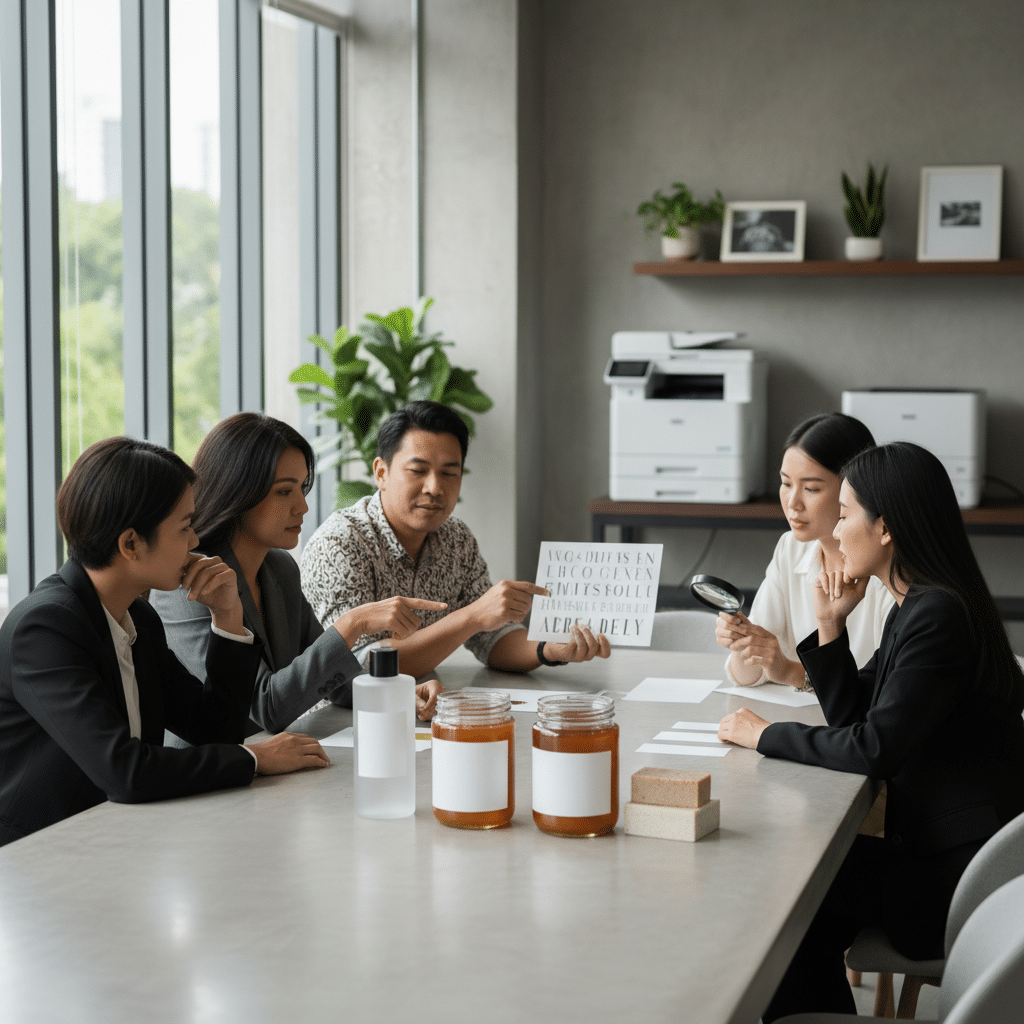
อัปเดต 2026! ทริคเลือกฟอนต์ฉลากสินค้าให้แบรนด์ดูแพง
การเลือกฟอนต์สำหรับฉลากสินค้าเป็นมากกว่าการเลือกตัวอักษรที่สวยงาม แต่คือกลยุทธ์สำคัญในการสื่อสารตัวตนของแบรนด์และสร้างการรับรู้ที่มีมูลค่าสูงในสายตาผู้บริโภค ฟอนต์ที่เหมาะสมสามารถยกระดับสินค้าธรรมดาให้ดูพรีเมียมและน่าเชื่อถือได้ ในทางกลับกัน ฟอนต์ที่เลือกผิดอาจทำให้แพ็กเกจจิ้งที่ออกแบบมาอย่างดีนั้นด้อยค่าลงได้ทันที
สรุปประเด็นสำคัญของการเลือกฟอนต์
- ความสอดคล้องกับแบรนด์: ฟอนต์ต้องสะท้อนบุคลิกและตำแหน่งทางการตลาดของสินค้าได้อย่างถูกต้อง เพื่อสร้างภาพลักษณ์ที่น่าเชื่อถือ
- ความเรียบง่าย: การใช้ฟอนต์ไม่เกิน 2-3 รูปแบบบนฉลากสินค้า ช่วยให้การออกแบบดูสะอาดตา เป็นระเบียบ และมีความพรีเมียม
- ความชัดเจนในการอ่าน: ฉลากสินค้าต้องให้ข้อมูลที่ชัดเจน ดังนั้นการเลือกฟอนต์ที่อ่านง่ายแม้มีขนาดเล็กจึงเป็นสิ่งสำคัญที่สุด
- การจัดวางอย่างมีชั้นเชิง: การใช้ขนาด น้ำหนัก และพื้นที่ว่างรอบตัวอักษรอย่างเหมาะสม ช่วยนำสายตาและสร้างความรู้สึกหรูหราให้กับการออกแบบ
- การเลือกตระกูลฟอนต์: ฟอนต์ตระกูล Serif ให้ความรู้สึกคลาสสิกและเป็นทางการ ในขณะที่ Sans-serif ให้ความรู้สึกทันสมัยและเรียบง่าย การเลือกใช้จึงขึ้นอยู่กับภาพลักษณ์ที่แบรนด์ต้องการสื่อสาร
เหตุผลที่ฟอนต์ส่งผลต่อภาพลักษณ์แบรนด์
ในโลกของการตลาดที่การแข่งขันสูง การสร้างแบรนด์ SME ให้โดดเด่นและเป็นที่จดจำนั้นมีความสำคัญอย่างยิ่ง ฉลากสินค้าเปรียบเสมือนด่านแรกที่สื่อสารกับลูกค้า และฟอนต์คือ “น้ำเสียง” ของแบรนด์ที่แสดงออกผ่านการออกแบบ ฟอนต์สามารถกระตุ้นความรู้สึกและสร้างการรับรู้ได้โดยที่ผู้บริโภคอาจไม่รู้ตัว เช่น ฟอนต์ที่มีเส้นสายโค้งมนอาจให้ความรู้สึกเป็นมิตรและเข้าถึงง่าย ในขณะที่ฟอนต์ที่มีเส้นตรง คมชัด อาจสื่อถึงความเป็นมืออาชีพ ความน่าเชื่อถือ และความทันสมัย
สำหรับผู้ประกอบการ การเลือกฟอนต์จึงเป็นขั้นตอนเชิงกลยุทธ์ที่ต้องพิจารณาอย่างรอบคอบในช่วงเริ่มต้นของการพัฒนาสินค้าหรือการปรับภาพลักษณ์แบรนด์ การเลือกฟอนต์ที่ไม่สอดคล้องกับบุคลิกของสินค้าอาจสร้างความสับสนและลดทอนความน่าเชื่อถือ เช่น การใช้ฟอนต์แนวสนุกสนานกับผลิตภัณฑ์สกินแคร์ระดับพรีเมียม อาจทำให้สินค้าดูไม่น่าไว้วางใจ ดังนั้น การทำความเข้าใจจิตวิทยาเบื้องหลังของฟอนต์แต่ละประเภทจึงเป็นเครื่องมือสำคัญที่ช่วยให้การออกแบบฉลากสินค้าสามารถเพิ่มมูลค่าและสร้างความประทับใจแรกที่แข็งแกร่งได้
หลักการพื้นฐานในการเลือกฟอนต์ฉลากสินค้าให้ดูแพง
การทำให้ฉลากสินค้าดู “แพง” ไม่ได้หมายถึงการเลือกใช้ฟอนต์ที่หรูหราหรือวิจิตรพิสดารเสมอไป แต่เกิดจากการผสมผสานองค์ประกอบหลายอย่างเข้าด้วยกันอย่างลงตัว เพื่อสร้างภาพรวมที่ดูดี มีรสนิยม และสื่อสารคุณค่าของแบรนด์ได้อย่างมีประสิทธิภาพ หลักการพื้นฐานต่อไปนี้เป็นแนวทางสำคัญสำหรับนักออกแบบและเจ้าของแบรนด์
จำกัดจำนวนฟอนต์: น้อยแต่มาก เรียบแต่โก้
หนึ่งในข้อผิดพลาดที่พบบ่อยในการออกแบบฉลากคือการใช้ฟอนต์หลากหลายรูปแบบมากเกินไป ซึ่งทำให้ฉลากดูสับสนและขาดความเป็นมืออาชีพ หลักการออกแบบสากลแนะนำให้จำกัดการใช้ฟอนต์บนชิ้นงานเดียวไว้ที่ไม่เกิน 2-3 รูปแบบ โดยแบ่งหน้าที่อย่างชัดเจน:
- ฟอนต์หลัก (Primary Font): ใช้สำหรับชื่อแบรนด์หรือชื่อสินค้า ซึ่งเป็นส่วนที่โดดเด่นที่สุด ควรเลือกฟอนต์ที่สะท้อนบุคลิกแบรนด์ได้ดีที่สุด
- ฟอนต์รอง (Secondary Font): ใช้สำหรับหัวข้อย่อยหรือคำอธิบายสั้นๆ ควรเป็นฟอนต์ที่เข้ากันได้ดีกับฟอนต์หลัก แต่อาจมีความแตกต่างเล็กน้อยเพื่อสร้างความน่าสนใจ
- ฟอนต์เนื้อหา (Body Font): ใช้สำหรับข้อมูลรายละเอียด เช่น ส่วนประกอบ วิธีใช้ หรือข้อมูลทางโภชนาการ ฟอนต์นี้ต้องเน้นความอ่านง่ายเป็นพิเศษ
การจำกัดจำนวนฟอนต์ช่วยสร้างความเป็นระเบียบและความต่อเนื่อง ทำให้ผู้บริโภคสามารถประมวลผลข้อมูลบนฉลากได้ง่ายขึ้น และยังส่งผลให้ภาพรวมของการออกแบบดูสะอาดตาและพรีเมียม
ความสอดคล้องกับบุคลิกของแบรนด์
ก่อนจะเลือกฟอนต์ สิ่งสำคัญคือต้องกำหนดบุคลิกของแบรนด์ (Brand Personality) ให้ชัดเจนก่อน แบรนด์ของคุณเป็นแบบไหน? คลาสสิก, ทันสมัย, ออร์แกนิก, สนุกสนาน, หรือหรูหรา? ฟอนต์ที่เลือกใช้ควรเป็นภาพสะท้อนของบุคลิกนั้นๆ
ฟอนต์ทำหน้าที่เปรียบเสมือน “เสียง” ของแบรนด์ การเลือกใช้ฟอนต์ที่ไม่เข้ากันก็เหมือนกับการพูดด้วยน้ำเสียงที่ไม่สอดคล้องกับข้อความที่ต้องการสื่อ ซึ่งจะทำให้ภาพลักษณ์ของแบรนด์ขาดความน่าเชื่อถือได้
ตัวอย่างเช่น สินค้าที่เป็นมิตรต่อสิ่งแวดล้อมอาจเหมาะกับฟอนต์ที่ให้ความรู้สึกเป็นธรรมชาติและเขียนด้วยมือ (Handwritten) เล็กน้อย ในขณะที่ผลิตภัณฑ์เทคโนโลยีอาจเหมาะกับฟอนต์ที่ดูสะอาด คมชัด และสื่อถึงอนาคต
เลือกตระกูลฟอนต์ให้ตรงโจทย์: Serif vs. Sans-serif
การทำความเข้าใจความแตกต่างระหว่างฟอนต์สองตระกูลหลักนี้เป็นพื้นฐานที่สำคัญที่สุดในการเลือกฟอนต์:
Serif: ความคลาสสิก สง่างาม และน่าเชื่อถือ
ฟอนต์ตระกูล Serif คือฟอนต์ที่มี “เชิง” หรือขีดเล็กๆ ที่ปลายตัวอักษร ซึ่งช่วยนำสายตาในการอ่านข้อความยาวๆ ฟอนต์กลุ่มนี้มักให้ความรู้สึกถึงประเพณี ความเป็นทางการ ความน่าเชื่อถือ และความหรูหรา จึงนิยมใช้กับแบรนด์ที่ต้องการสร้างภาพลักษณ์ที่ดูดีมีระดับ เช่น แบรนด์สินค้าลักชัวรี, ไวน์, หนังสือ หรือสถาบันการเงิน
Sans-serif: ความทันสมัย เรียบง่าย และมินิมอล
“Sans” เป็นภาษาฝรั่งเศส แปลว่า “ไม่มี” ดังนั้น Sans-serif จึงหมายถึงฟอนต์ที่ไม่มีเชิง ทำให้ตัวอักษรดูเรียบง่าย สะอาดตา และทันสมัย ฟอนต์กลุ่มนี้ให้ความรู้สึกเป็นมิตร เข้าถึงง่าย และมีความร่วมสมัย เหมาะสำหรับแบรนด์ที่เน้นนวัตกรรม, สินค้าเพื่อสุขภาพ, ผลิตภัณฑ์สำหรับคนรุ่นใหม่ หรือแบรนด์ที่ต้องการภาพลักษณ์แบบมินิมอล
ให้ความสำคัญกับความอ่านง่ายเป็นอันดับแรก
ไม่ว่าฟอนต์จะสวยงามเพียงใด หากลูกค้าไม่สามารถอ่านข้อมูลบนฉลากได้อย่างชัดเจน การออกแบบนั้นก็ถือว่าล้มเหลว ความอ่านง่าย (Readability) คือปัจจัยที่สำคัญที่สุด โดยเฉพาะบนพื้นที่จำกัดของฉลากสินค้าซึ่งมักจะต้องบรรจุข้อมูลสำคัญไว้มากมาย ควรพิจารณาปัจจัยต่างๆ เช่น ขนาดตัวอักษรต้องไม่เล็กเกินไป, ความหนาของเส้นต้องพอดี (ไม่บางจนขาดหายเมื่อพิมพ์), และช่องไฟระหว่างตัวอักษร (Kerning) และระหว่างบรรทัด (Leading) ต้องเหมาะสม